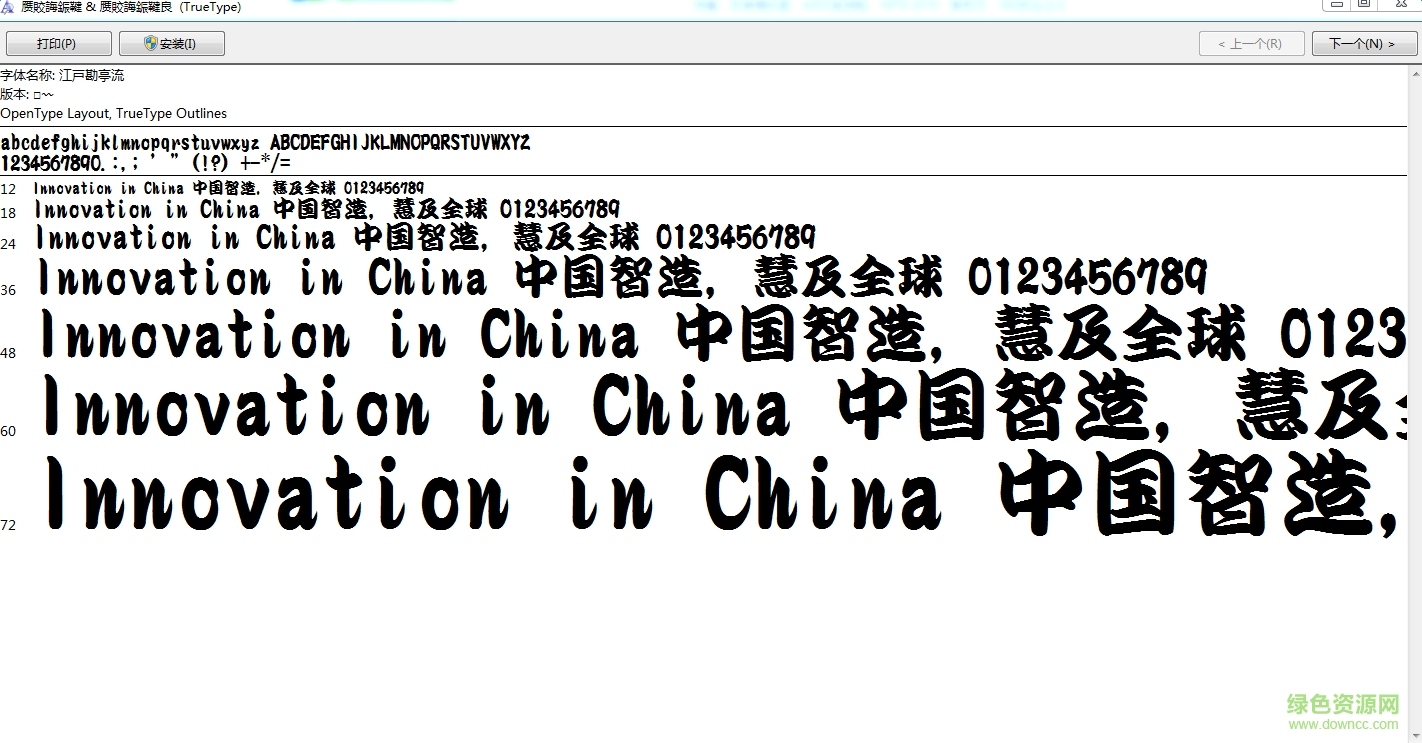
江戶勘亭流字體是一款圓潤、敦厚的字體,線條柔和,筆畫粗黑,整體效果十分醒目,喜歡該字體的小伙伴快來綠色資源網(wǎng)下載吧!
勘亭流體屬于江戶文字,是一種江戶時代(大體相當(dāng)于我國明末清初那段時間)所使用的廣告字體。勘亭流是使用于落語(類似中國的單口相聲)、歌舞伎等的招牌或節(jié)目表的字體。由戲劇界人物岡崎屋勘六設(shè)計,勘亭流就是得名自其別號“勘亭”。